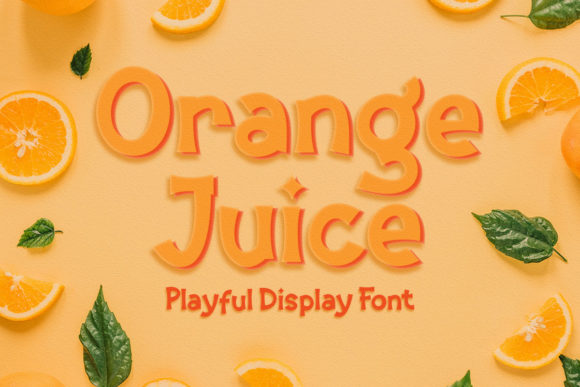
Creativefabrica Orange Juice Font
[Creativefabrica] Orange Juice Font
Оранжевый сок - это простой и удобный шрифт для отображения на дисплее.
Оранжевый сок будет выглядеть превосходно в любом контексте, независимо от того, используется ли он на оживленном фоне или в качестве самостоятельного заголовка!